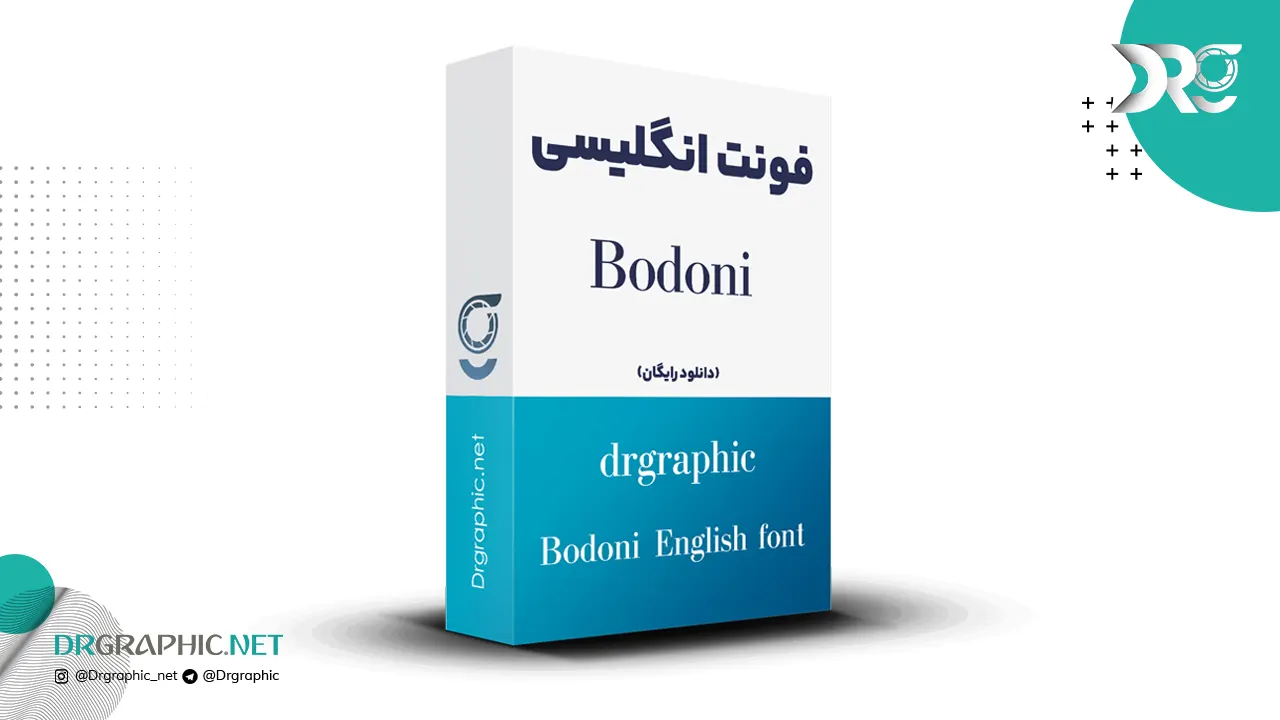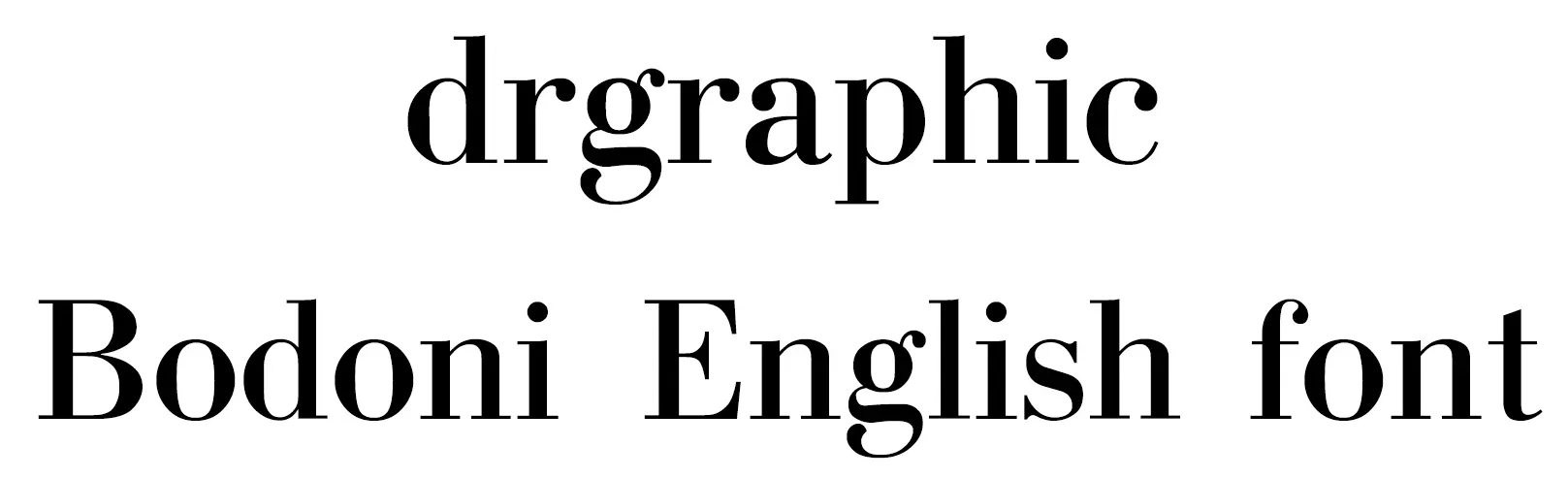
محصول فوق فونت انگلیسی Bodoni میباشد که کاربرد بسیار زیادی در انواع متن های انگلیسی دارد ، و یک فونت انگلیسی کاملاً زیبا با طراحی دوست داشتنی است.
نمونه نوشته با این فونت: